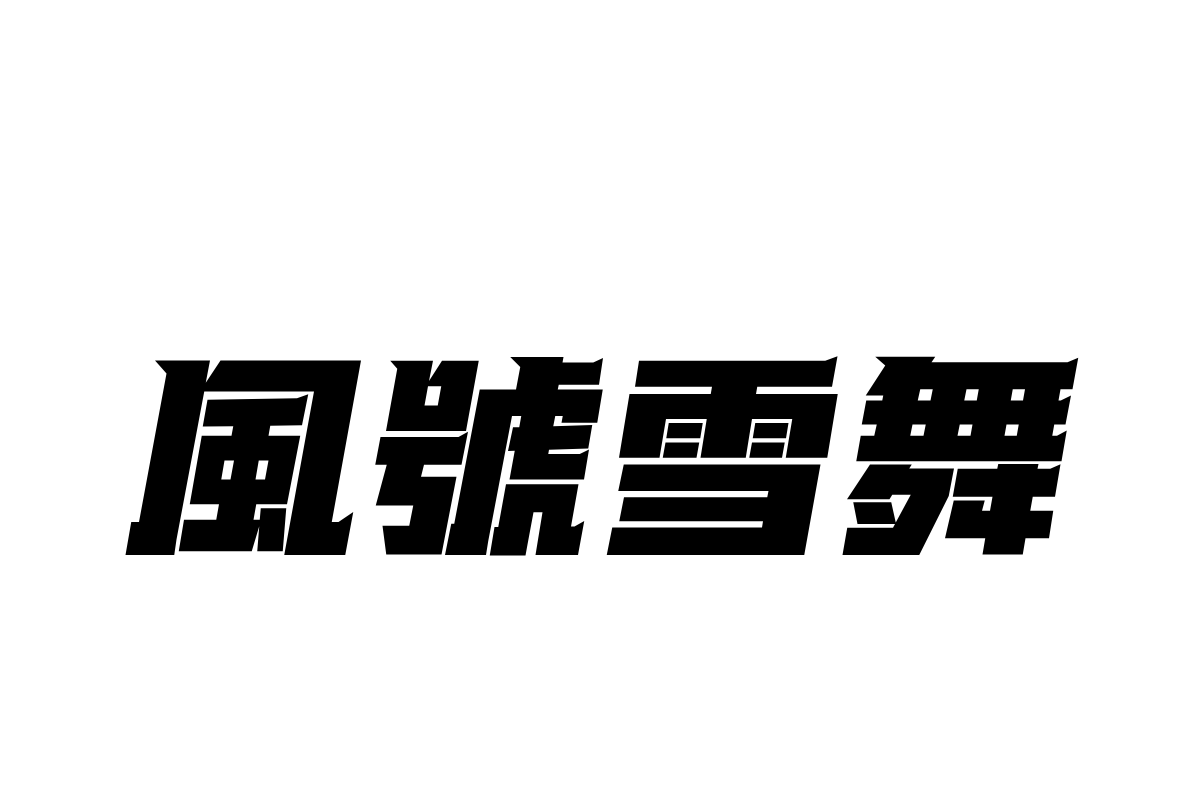
汉仪星河舰队105繁体是一款具有现代感的中文字体。这款字体的设计灵感来源于宇宙中的星系,通过独特的字形结构和笔画变化,呈现出一种深邃、广阔的视觉效果。
字体特点:
1. 字形结构独特:汉仪星河舰队105繁体采用了独特的字形结构,使得文字在视觉上更加富有层次感和立体感。
2. 笔画流畅:该字体的笔画设计流畅自然,无论是书写还是阅读,都能带来舒适的体验。
3. 易于识别:汉仪星河舰队105繁体采用了简洁明了的设计,使得文字在各种场景下的辨识度都非常高。
4. 适应性强:这款字体适用于多种应用场景,如书籍、杂志、海报、网页等,能够满足不同用户的需求。
总的来说,汉仪星河舰队105繁体是一款具有现代感和实用性的中文字体,适合用于需要强调视觉效果和提升用户体验的设计项目中。